教育部和北京大学再次续约共建中国文字字体设计与研究中心
2023年9月22日,国家语委研究型基地续建签约会议在教育部北楼举行。教育部语言文字信息管理司司长田立新、北京大学副校长张锦分别代表双方单位签字,续约共建国家语委中国文字字体设计与研究中心(以下简称字体中心)。教育部语言文字信息管理司也分别与北京师范大学、中国传媒大学、鲁东大学续约,继续共建中国文字整理与规范研究中心、国家语言资源监测与研究有声媒体中心、汉语辞书研究中心。
田立新司长、张锦副校长签字续约共建中国文字字体设计与研究中心
续约签字仪式由教育部语言文字信息管理司副司长刘宏主持,教育部语言文字信息管理司司长田立新对国家语委研究型基地的建设工作做了指导发言。她表示:近年来,各机构围绕国家语言文字事业的发展需求、语言文字学术发展的热点与趋势,聚焦各自的核心优势领域,取得了重要的进展,发布了一大批重要的研究型成果,研究水平进一步提升,影响力不断扩大。同时,各机构在建设当中也特别注重发挥资政建言的重要作用,不仅为国家语言文字事业提供了科研支撑和决策支持,同时也为教育事业和语言文字事业的高质量发展做出了积极的贡献。
田司长宣读了专家对“字体中心”的考察评审意见:字体中心持续推进字体生成与字库制作基础理论研究,通过“中华精品字库工程”“中华字库工程”“北京冬奥定制字体”等重大工程开发了一系列重要成果,有效服务社会使用需求,助力文化自强自信,也对字体中心提出了进一步要求。
最后,田司长对续建签约的研究型基地提出了四项具体要求:一是各依托单位要进一步加大政策支持力度,将研究型基地建设纳入学校整体建设发展规划,按照教育部人文社会科学重点研究基地建设规格给予配套支持;二是要进一步提升资政服务能力,强化智库建设,要聚焦国家重大战略、教育和语言文字事业发展的重点问题,牢固树立国家意识和问题意识,敏锐捕捉语言生活中的重要问题,及时提出思路方案,向政府有关部门提供高水平的资政建议和服务;三是进一步加强人才培养,打造一支结构合理、业务精良、专兼结合、互补融合的学术团队;四是进一步加强标志性成果的产出、转化和应用,要扎根中国本土,增强国际意识,瞄准学科前沿,打造前瞻性、标志性成果,要加强协同创新,提升承担大型研究任务、重大工程的能力,推动成果的高质量转化和应用,提升服务国家战略和地方发展的能力。
国家语委研究型基地续建签字仪式会场
北京大学副校长张锦院士在发言时表示:教育部语信司和北京大学于2005年起合作共建“中国文字字体设计与研究中心”,现开始进入第四个建设周期,非常感谢教育部语信司对北京大学的信任和支持。北京大学从上世纪70年代开始研究计算机字库技术,王选教授发明的汉字字形信息高倍率压缩、高速还原输出等专利技术,成功解决了计算机处理中文的难题,引发了我国印刷出版行业“告别铅与火、迎来光与电”的革命,取得了巨大的经济效益和社会效益,创造了“产学研”相结合的典范。中国文字字体设计与研究中心成立十八年来,在教育部语信司的指导下,在中文字体设计领域取得了一些重要进展。发言中,张锦副校长详细介绍了字体中心做出的突出工作和建设成果。
北京大学副校长张锦院士发言
中国文字字体设计与研究中心于2005年4月29日成立,由教育部语言文字信息管理司和北京大学共同建设,由北京大学王选计算机研究所和北京北大方正电子有限公司承担建设任务。字体中心是对中国文字(包括汉字和少数民族文字)进行字体研究、设计和制作的机构,旨在研究与发展新的字体技术与方法,不断地向社会推出符合文字规范的、优美的新字体,中心承担中国文字字体研究与设计、字库制作、以及字形规范示范宣传与推广等方面的任务,完成国家、部委规定的相关科研项目。2018年初,教育部语言文字信息管理司和北京大学签署了续建协议,自续建以来,字体中心在中文字体设计领域的多个方面都做出了突出成果。
在国家重点工程方面,字体中心承担建设作为中华优秀传统文化传承发展工程支持项目的“中华精品字库工程”,目前已发布40款名家书法字体,同期启动公益应用计划,助力书法经典融入大众生活;参与国家新闻出版重大科技工程项目“中华字库工程”,开发完成30万字的宋体和楷体成果字库。在技术研究方面,中心承担多个国家与省部级科研项目,在大规模手写体中文字库自动生成、高质量矢量字形合成、字形纹理特效风格迁移等方面取得重要进展,研发成功中文字库辅助设计与自动生成相关系统,显著提升各类字库的制作效率。在服务社会方面,积极参与语言文字规范化工作,设计开发了国家《通用规范汉字表》的配套字库;设计开发的北京冬奥定制字体在北京冬奥会和冬残奥会正式使用;参与GB18030国家标准的制定工作,最新研制的人口信息超大字库已在第二代居民身份证、护照等众多系统中使用;设计推出的各种风格的字体得到社会各界的广泛应用;利用人工智能技术助力书法教学,通过墨韵智能项目帮扶贫困地区和书法教育薄弱地区学校。在人才培养方面,字体中心将产学研相结合,在参与国家级青年人才计划、培养硕博士研究生等方面均有建树。
中华精品字库工程已经发布了甲骨文、颜真卿楷书等40款历代书法名家字体
北京冬奥定制字体在北京冬奥会和冬残奥会正式使用
字体中心持续升级完善人口信息超大字库,解决社会系统中人名缺字问题
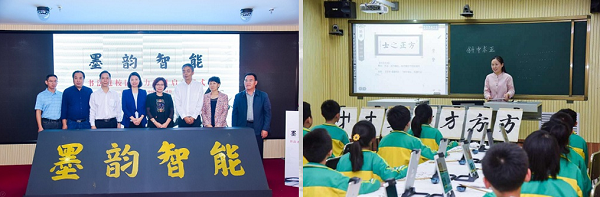
字体中心通过墨韵智能项目帮扶贫困地区和书法教育薄弱地区学校
在下一个共建周期,字体中心将进一步发挥北京大学王选计算机研究所、北京北大方正电子有限公司在文字信息处理技术和字体设计方面的优势,在教育部语信司和各位专家的指导下,致力于引领中文字体设计和技术发展,加强字体审美标准评价和治理研究,努力研发更多优质的中文字库,推广规范使用汉字,满足社会各界不同的用字需求,为中华汉字文明的传承和发展尽一份力量。
教育部语信司标准处二级巡视员王丹卉,规划协调处处长李强,标准处副处长郭浩、张嵩,以及北京大学科研部副部长李晓强,北京大学王选计算机研究所副所长、中国字体设计与研究中心主任郭宗明,北京北大方正电子有限公司董事长兼总裁邵行等出席并见证了续约签字仪式。